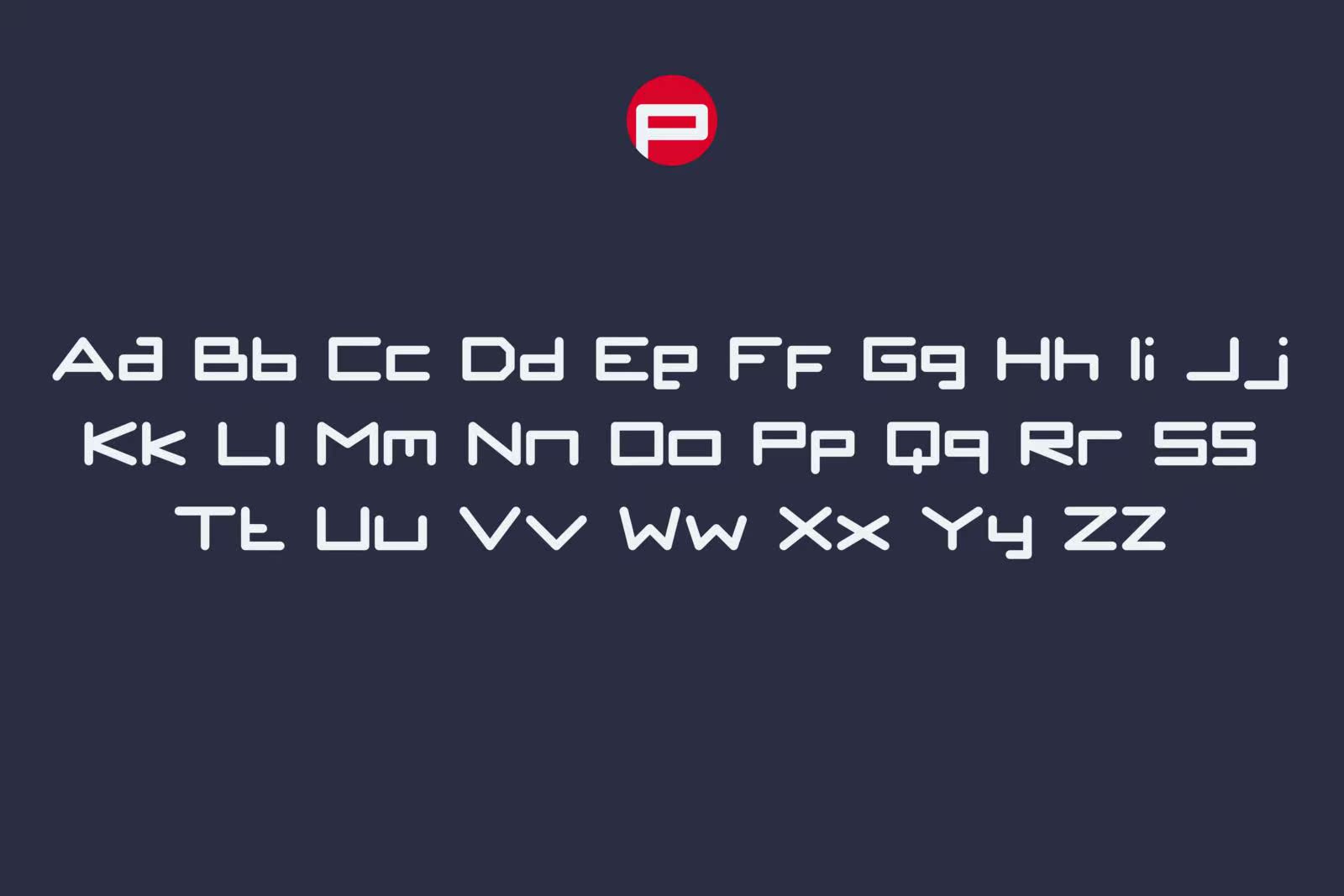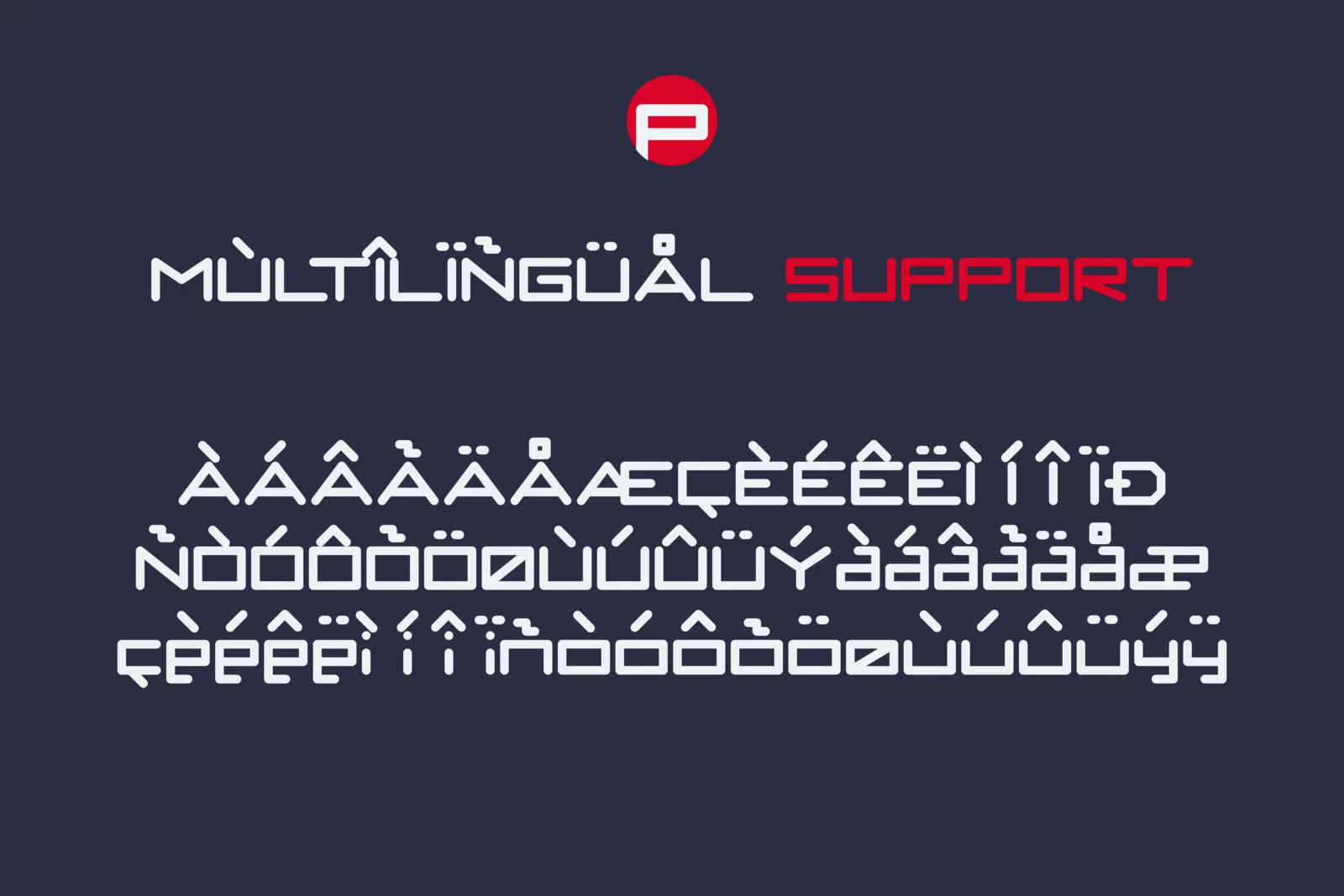
Parosh Cai具有开放性和现代化的显示字体。该字体支持英语语言加上完全通用的多语言和标准标点符号。Parosh Cai适用于标志设计、书皮、杂志等。Parosh Cau适用于各种设备,如Windows、Mac、,Linux。使用Paroshca.Paroshcai字体和现代显示字体立即美化您的设计。此字体支持英语加上完全通用的多语言和标准标点符号。Paroshcai适用于徽标设计、书皮、杂志等。Paroshcaus支持各种设备,如Windows、Mac、,Linux.ImmediatelybeautifyyourdesignswithParoshca。